Vienna Typeface: Typografie als Stadtführung
Stell dir vor, du kannst die Stadt Wien nicht nur sehen, sondern auch sprichwörtlich lesen. Vienna Typeface nimmt dich genau auf diese Reise mit. Das Projekt zeigt das lateinische Alphabet und dessen Buchstaben in einer dreidimensionalen Hommage an die österreichische Hauptstadt. Jeder der illustrierten Buchstaben ist eine 3D-Miniatur, die einen Aspekt der Wiener Lebenskultur, ein Detail oder eine Sehenswürdigkeit zum Thema nimmt und in einer Art Diorama darstellt. Die 26 Schriftzeichen dienen dabei als illustrierte Schaukästen der Stadt, in denen Elemente mit modellähnlicher Detailverliebtheit dargestellt werden. Es ist eine visuelle Erzählung, die die kulturelle und historische Vielfalt Wiens in 26 Buchstaben einfängt.
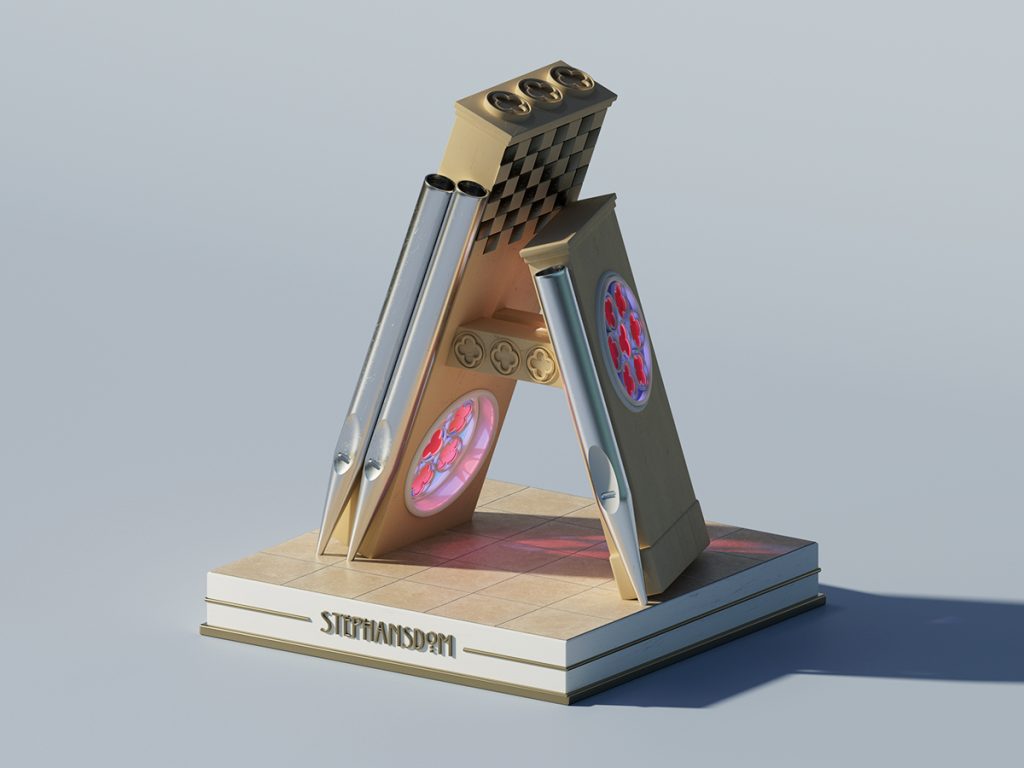
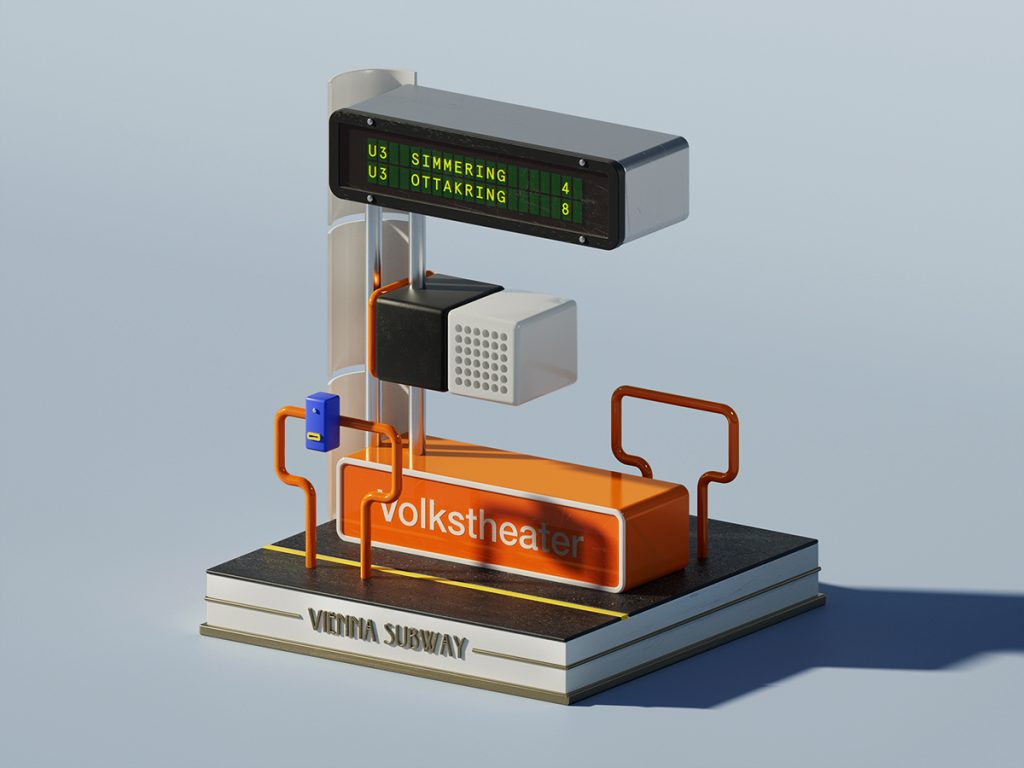
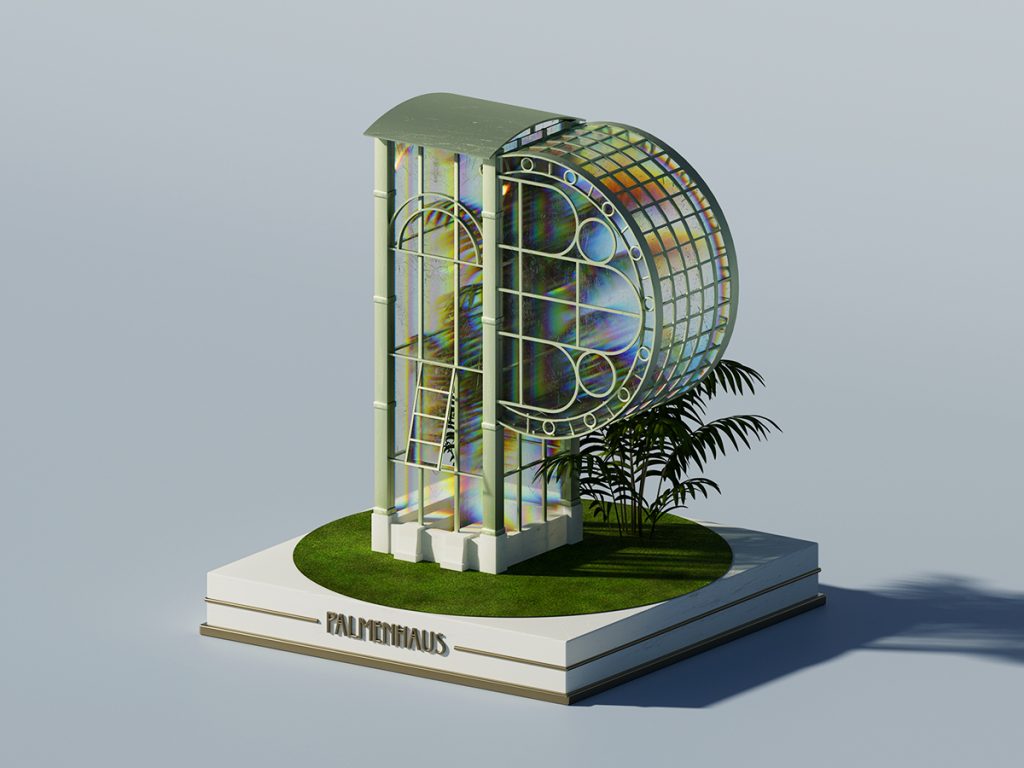
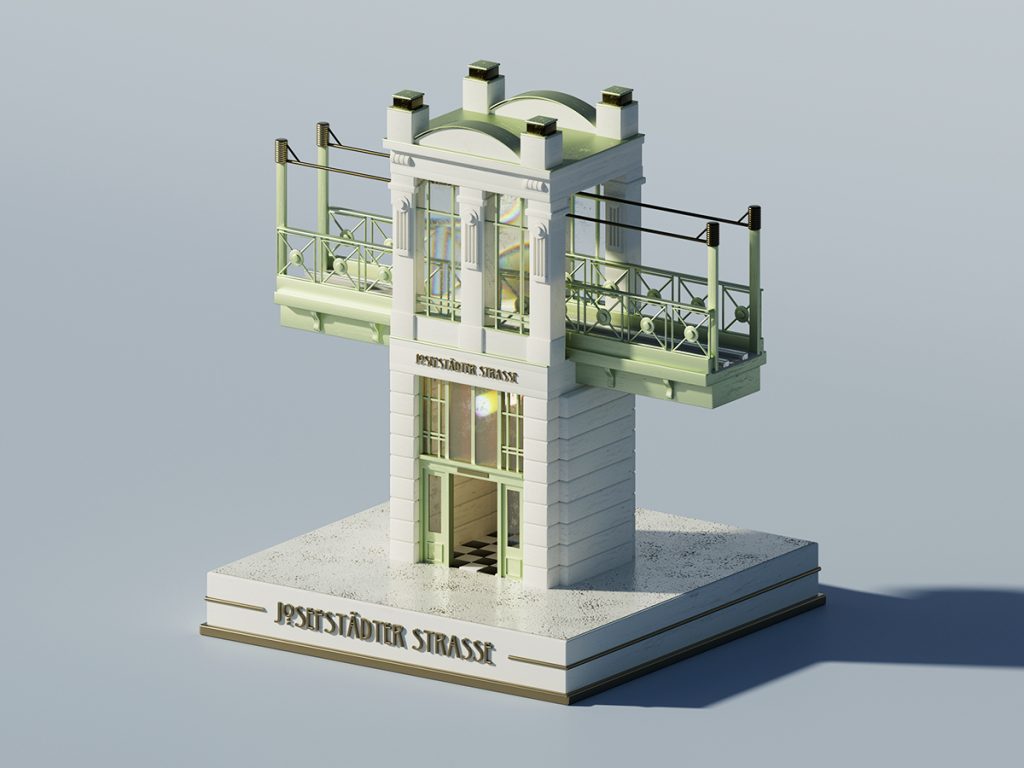
"Das könnte das Stadtmarketing völlig neu definieren", erklärt der 3D-Designer Ricardo Gantschnigg und eröffnet damit eine spannende Perspektive für alle Kommunen. Jeder Buchstabe erzählt einen interessanten Aspekt der Lebenskultur der Stadt oder zeigt eine Sehenswürdigkeit in innovativer Form. Die Stadt wird erlebbar.
In einer Zeit, in der sich Regionen zunehmend als touristische Erlebnisdestinationen positionieren, kann das Vienna Typeface beispielgebend für innovative Marketingstrategien sein. Tourismusdestinationen können sich als Erlebnisregionen positionieren und auf völlig neue Art und Weise BesucherInnen inspirieren und neugierig machen.
Darüber hinaus eröffnen die einprägsamen Visuals auch Potenzial für Merchandise-Produkte, bei denen die ikonischen 3D-Buchstaben als Design für Souvenirs, Poster oder individuelle Accessoires verwendet werden könnten – eine zusätzliche Möglichkeit, die Stadtmarke zu stärken und Touristen eine greifbare Erinnerung mitzugeben.
Typografie meets 3D
Das Besondere an diesem Projekt: Die Potenziale digitaler Gestaltung und Technologie wurden voll ausgeschöpft. Die Schrift wurde vollständig in einem 3D-Programm entwickelt und visualisiert. Dieser Ansatz zeigt, dass Typografie nicht auf flachen Oberflächen beschränkt sein muss. Indem Ricardo Gantschnigg dreidimensionale Miniaturen erschafft, bringt er das klassische Schriftdesign in eine neue Dimension. Die Buchstaben des Vienna Typeface sind nicht einfach grafische Elemente – sie sind Skulpturen, die eine Geschichte erzählen. Schrift wird hier nicht nur als Kommunikationsmittel verstanden, sondern auch als kreatives Ausdrucksmedium. Gantschnigg verbindet dabei zwei Welten: die handwerkliche Präzision eines Typografen und die experimentelle Freiheit eines 3D-Künstlers.
Die Möglichkeiten von 3D-Technologie sind noch nicht ausgeschöpft: Durch den Einsatz von Virtual Reality (VR) und Augmented Reality (AR) bietet das Projekt spannende Möglichkeiten: Touristen könnten mithilfe von AR direkt vor Ort die Buchstaben des Vienna Typeface als interaktive, virtuelle 3D-Skulpturen erleben – platziert an den realen Sehenswürdigkeiten Wiens. VR könnte es ermöglichen, von zu Hause aus durch die Stadt zu reisen und dabei die Buchstaben in einer virtuellen Umgebung zu erkunden. Diese immersive Form des Storytellings macht die Stadt auf neue Weise erfahrbar.
Das Potential dreidimensionaler Gesaltung – auch für Marken
Die 3D-Illustration eröffnet völlig neue Möglichkeiten in der visuellen Kommunikation. Sie bietet nicht nur eine beeindruckende Tiefe und Detailtreue, sondern auch eine größere Flexibilität, um komplexe Ideen und Konzepte darzustellen. Durch die dreidimensionale Gestaltung lassen sich abstrakte Ideen greifbarer machen, und Produkte, Räume oder Szenen können realitätsnah simuliert und in ihrer Umgebung verankert werden. Besonders im Branding birgt die 3D-Illustration enormes Potenzial: Sie ermöglicht es Marken, sich mit unverwechselbaren Designs – zum Beispiel in der Form von Keyvisuals – vom Wettbewerb abzuheben und eine einzigartige visuelle Sprache zu entwickeln. Von Produktvisualisierungen über Verpackungsdesign bis hin zu interaktiven Marketingkampagnen: 3D-Illustrationen sind nicht länger nur ein ästhetisches Element. Einmal erstellt, können sie leicht für Animationen adaptiert werden und so schnell sowie kosteneffizient an verschiedenen digitalen Touchpoints als Video für Kunden eingesetzt werden.
Vienna Typeface goes international
Das Projekt hat nicht nur die Herzen vieler Wiener erobert, sondern auch die Aufmerksamkeit der internationalen Design-Community auf sich gezogen. So wurde Vienna Typeface beim Joseph Binder Award 2022, einem der renommiertesten Illustrations- und Designwettbewerbe Österreichs, ausgezeichnet.
nternationale Anerkennung erhielt das Projekt auch mit dem TDC 69 Award – einem der wichtigsten Typografiepreise weltweit. Gleich zweimal wurde Vienna Typeface hier prämiert und zeigt damit, dass sich Design aus Österreich problemlos mit internationalen Maßstäben messen kann. Der TDC-Award, der vom Type Directors Club in New York verliehen wird, hebt Projekte hervor, die Schriftgestaltung neu definieren – und genau das tut Vienna Typeface. Es ist nicht einfach nur eine Schriftart, sondern eine dreidimensionale, künstlerische Interpretation einer ganzen Stadt.
Auch bei anderen internationalen Wettbewerben machte das Projekt Furore. Es gewann einen Merit Award beim Art Directors Club 2023 in New York und holte Bronze beim Art Directors Club in Deutschland.
Aber was macht diese Buchstaben so besonders? Nehmen wir zum Beispiel den Buchstaben A, der den Wiener Stephansdom repräsentiert – eine Symbiose aus verschiedenen Architekturstilen und farbenprächtigen Fenstern. Oder das E, das von den scheinbar banalen Dingen des Wiener Alltags inspiriert ist, wie der U-Bahn-Linie U3. Jeder Buchstabe erzählt seine eigene Geschichte. Das P verweist auf das historische Palmenhaus Schönbrunn, während das T die kunstvollen Details der Art Nouveau-Architektur an der U-Bahn-Station Josefstädter Straße einfängt.
Das Vienna Typeface ist mehr als nur Design – es ist eine Liebeserklärung an eine Stadt. Eine Stadt, die Tradition und Moderne so harmonisch vereint wie ihre eigene Typografie.